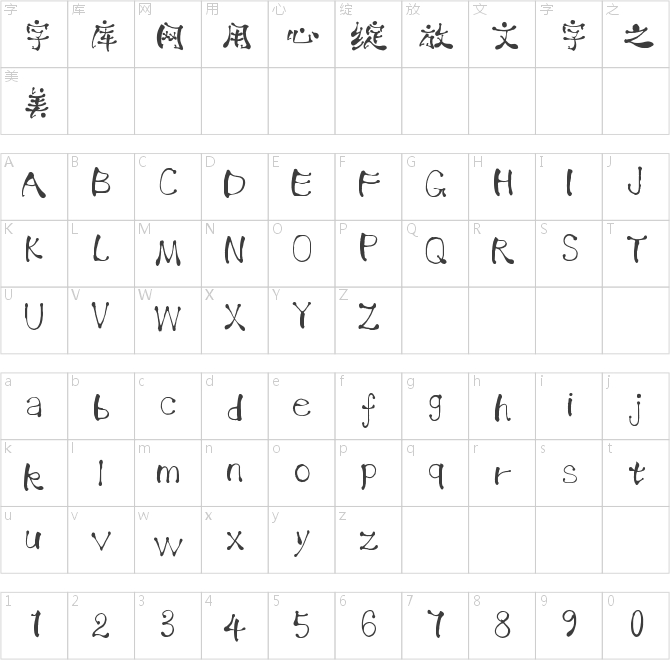
字魂253號-萌趣跳跳蛙
• 字魂253號-萌趣跳跳蛙是一款可愛的手寫字,字體結構巧妙活潑,筆畫粗細對比明顯,橫細豎粗,字體的點筆畫多數呈圓點狀。字體風格上給人一種偏可愛、萌新的感覺。
字魂253號-萌趣跳跳蛙字體zihun253hao-mengcutiaotiaowa字庫是一款讓人賞心悅目、百看不厭的中文字體,適合各類廣告和產品包裝設計應用,字體大小21.21MB,格式為ttf字體,上傳用戶是東方時尚,作者/版權方為字魂